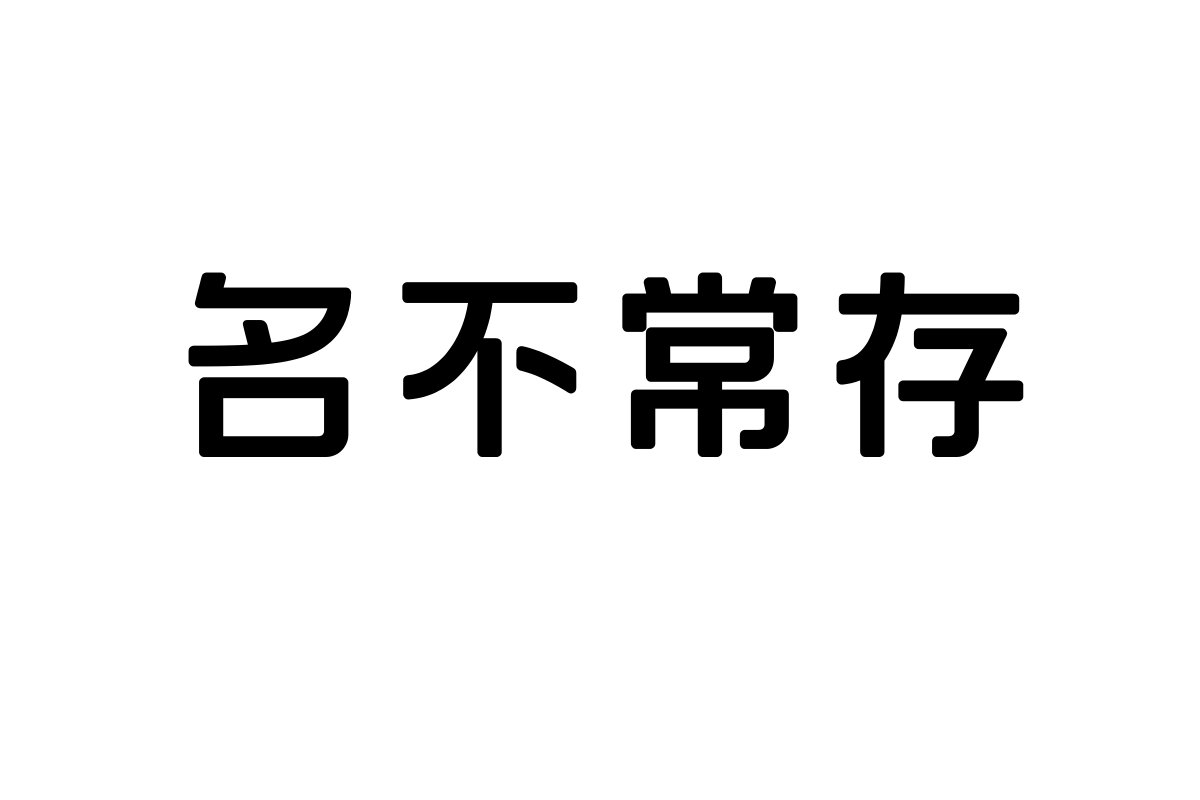
上首元气体字体是一款免费的中文字体,由上海字库有限公司开发。这款字体以其独特的设计风格和优美的线条而受到广泛欢迎。
上首元气体字体的笔画流畅,字形优美,给人一种优雅的感觉。它的字体结构紧凑,线条清晰,适合用于各种设计项目,如广告、海报、网页等。此外,这款字体还具有较好的可读性和易用性,适用于需要强调文字信息的场合。
上首元气体字体的应用场景非常广泛,包括商业广告、企业宣传、产品包装、网站设计等。无论是在印刷品还是电子屏幕上,这款字体都能够展现出其独特的魅力。